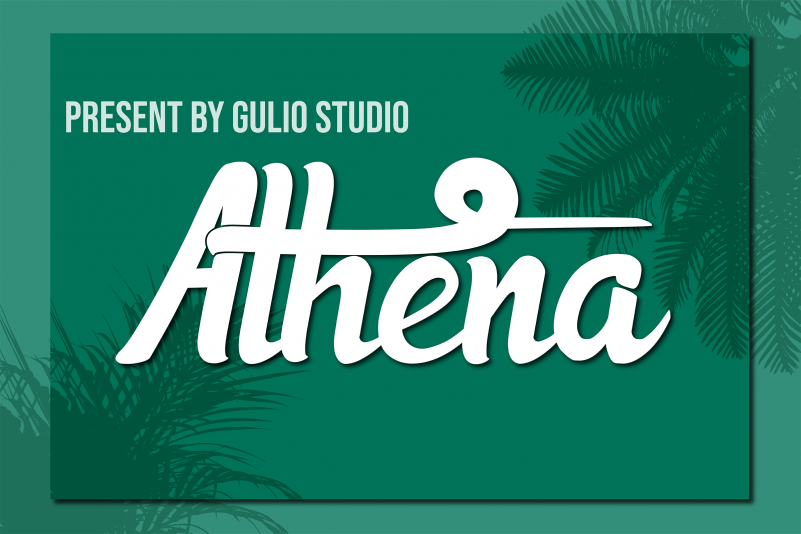
Athena Script Font – Download Grátis
Athena Script é uma fonte brush semelhante ao nosso dia a dia, inspirado na lindeza sagrada da Athena, a deusa do conhecimento e beleza. Embora não seja um texto formal, sua elegância natural cria um entrelazamento rico em detalhes que dá vida a qualquer design. Desenvolvida pelo designer GulioSt, a Athena Script oferece uma interação única entre a beleza simples e o encanto mais sofisticado. Com seu estilo brush, a fonte proporciona uma aparência atemporal sem deixar de lado o toque moderno que atualiza estilos clássicos. Seja para adicionar um pouco de encanto aos títulos ou dar forma à textura dos subtítulos, Athena Script é perfeita para criações criativas e convidativas. Com suas linhas suaves e sua presença elegante, a fonte traz uma sensação única e misteriosa que se adapta a qualquer projeto, tornando-a um recurso indispensável para aqueles buscando criar designs autênticos e memoráveis. Seja você criador de arte digital ou estilista gráfico, Athena Script é certamente um complemento valioso na sua paleta de recursos. Com seu design único e sofisticado, esta fonte se destaca como uma opção inovadora para qualquer projeto que esteja buscando expressar elegância em formato tipográfico.